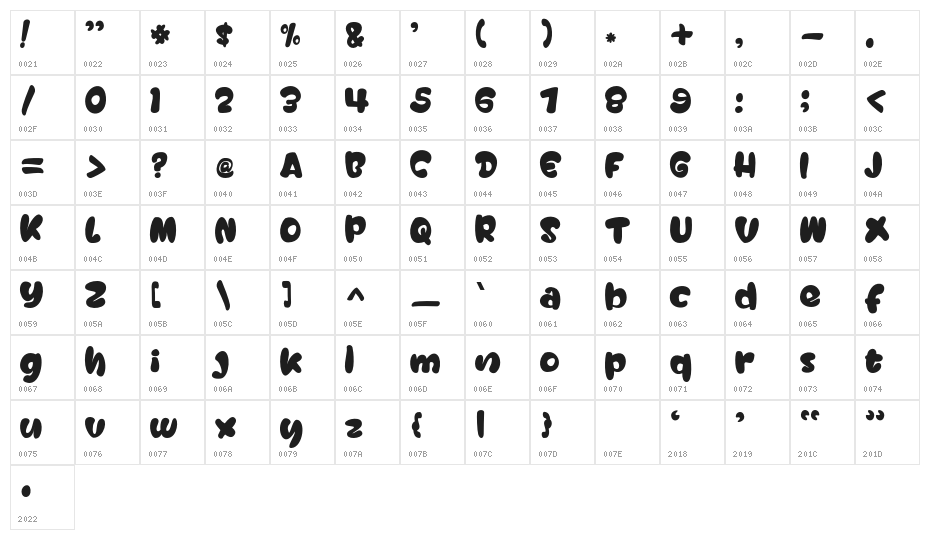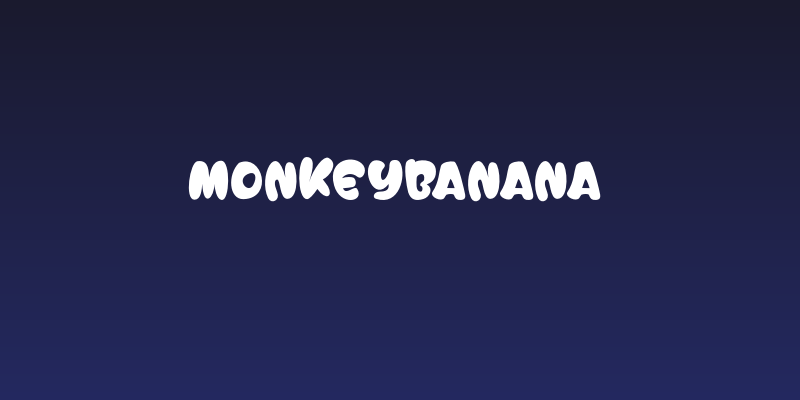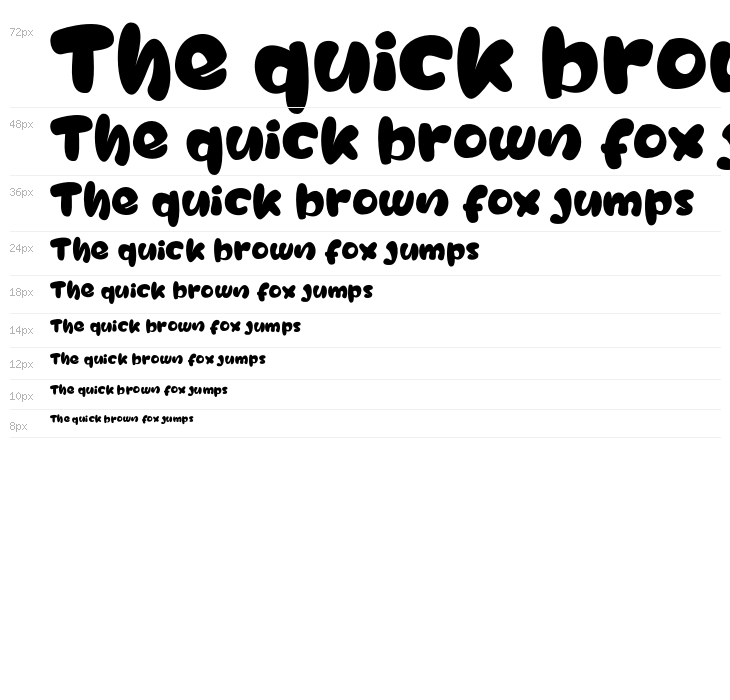
MonkeyBanana Font
✎ Cartoon
| Categorie | Cartoon |
| Stile generale | Playful, Whimsical |
| Progetti proposti | Ideal for children's books, playful branding, party invitations, and creative posters. |